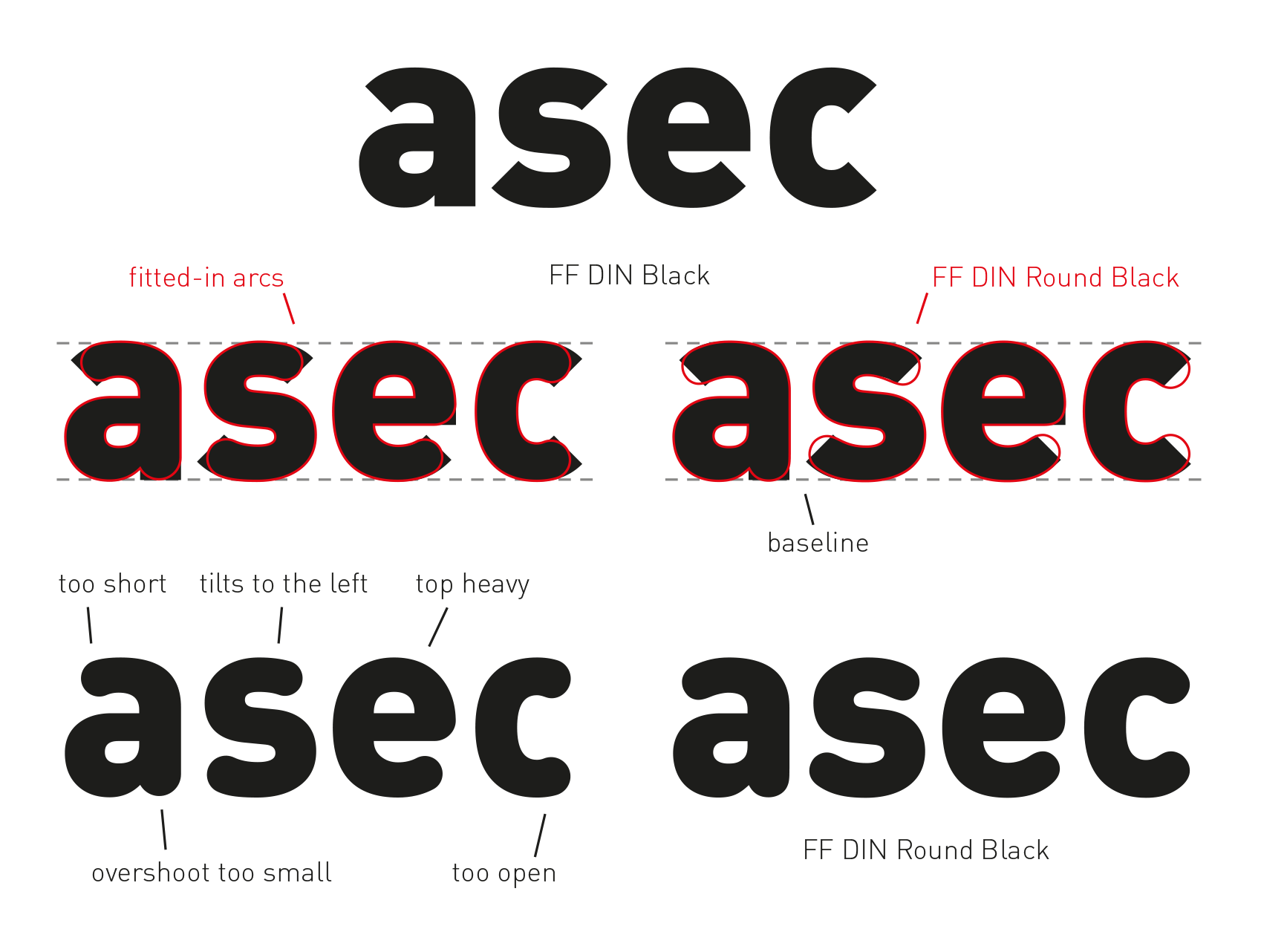
- 2010
- sans
- Antiqua statisch
- Versaleszett:
- enthalten
- Schriftsippe:
- zutreffend
Die FF DIN Round ist die erste Erweiterung der FF-DIN-Familie aus dem Jahr 2010. Die Schriftsippe besteht mittlerweile aus FF DIN (1995), FF DIN Round (2010), FF DIN Slab (2022) und FF DIN Stencil (2022). Die FF DIN Round verfügt über fünf Strichstärken, die mit denen der übrigen Familienmitglieder übereinstimmen. Neben einem ausgebauten lateinischen Zeichensatz unterstützt sie auch das kyrillische Schriftsystem. Mit dem Stylistic Set bzw. Formatsatz »German Capital Sharp S« (Stylistic Set 13 bzw. Satz 13) erhält man statt dem Doppel-S das Versaleszett (ẞ).
FF DIN Round Familie: Light—Black
FF DIN Black Versalien
FF DIN Round Familie: Light—Black
Aus FF DIN wird FF DIN Round
FF DIN Round Kyrillisch